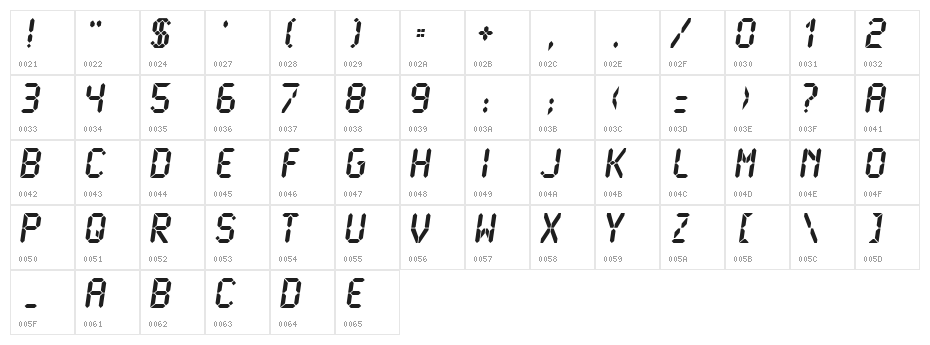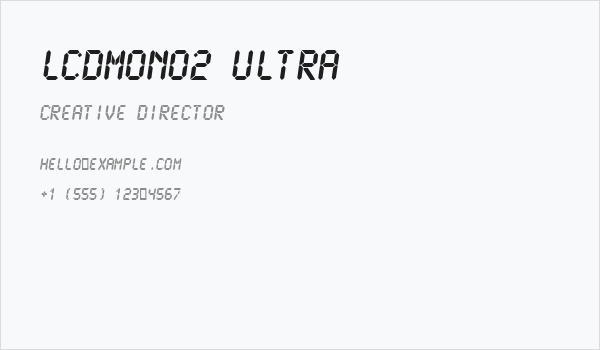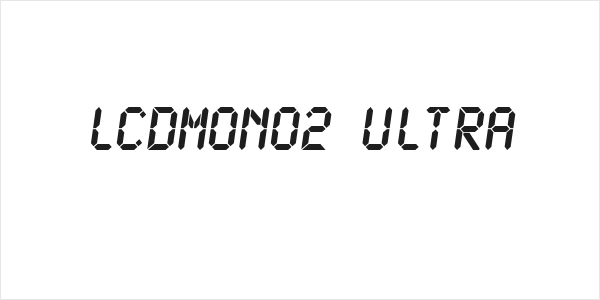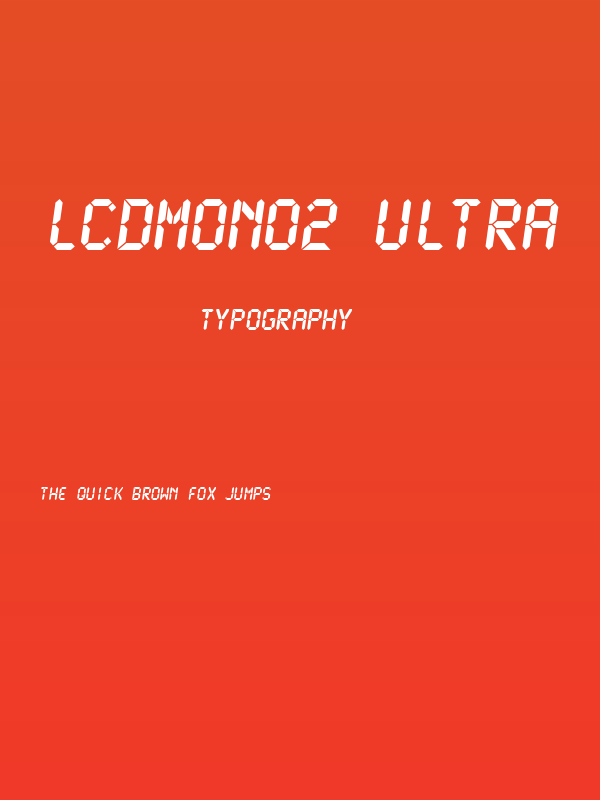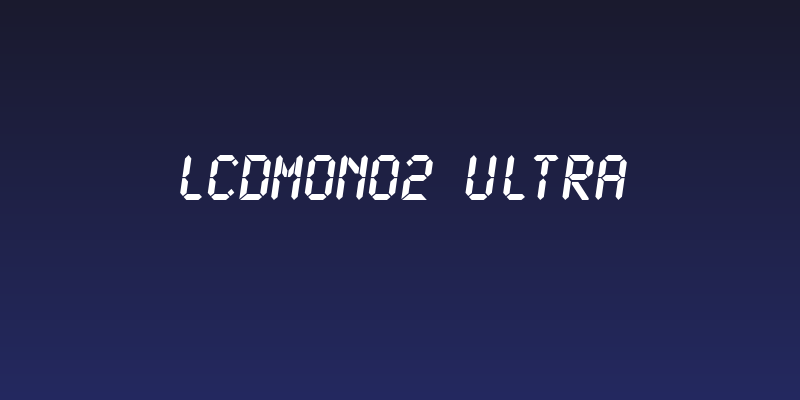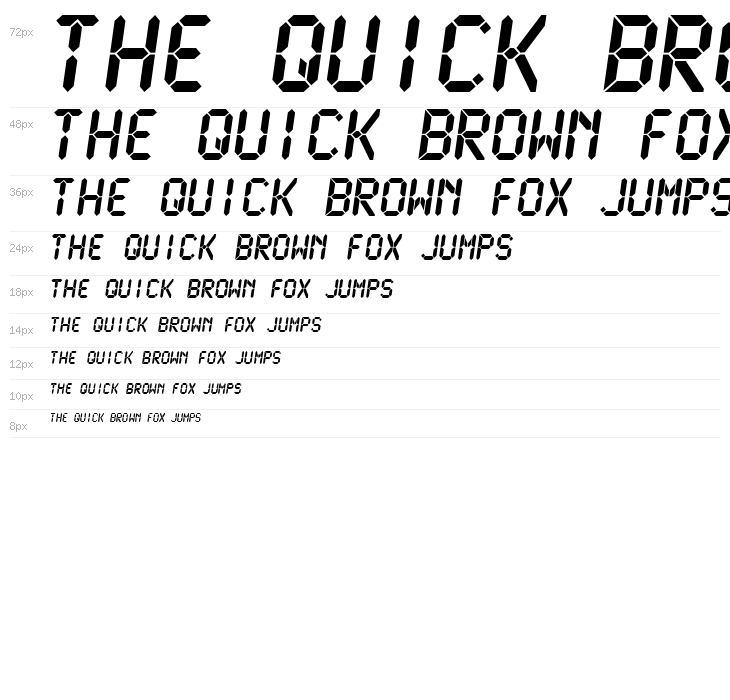
LCDMono2 Ultra Font
| Caz de utilizare | Logos, Headlines, Digital interfaces |
| Proiecte propuse | Ideal for digital-themed designs, tech-related branding, retro-futuristic posters, and electronic device interfaces. |